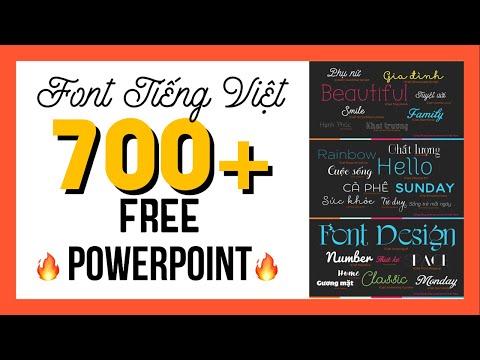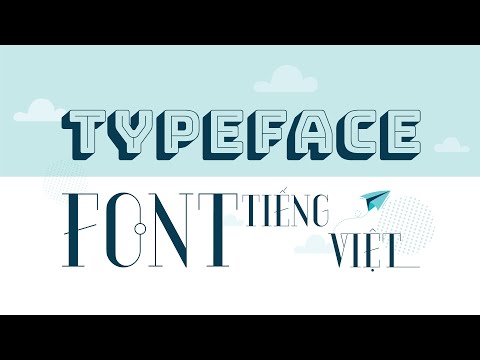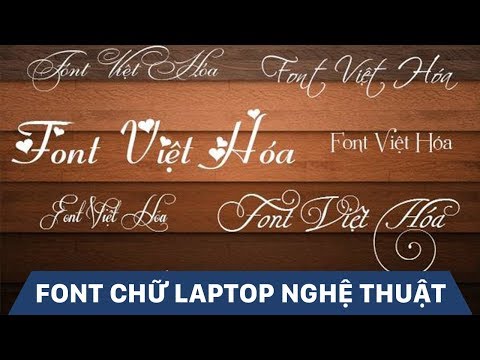
Tổng hợp các font chữ tiếng Việt đẹp trong Word update 2022
Novelty (font cách điệu): Tự nhiên, vui vẻ. Grunge (font bụi bặm): Mạnh mẽ, bí ẩn. Tặng bạn : 99+ Mẫu Font chữ làm biển quảng cáo. Font Chữ Tiếng Việt Đẹp Cho Thiết Kế giúp cảm nhận của người xem tốt
Dec 14, 2021100+ font chữ đẹp, hỗ trợ Tiếng Việt cho Word, Excel, Photoshop. I. Font văn bản 1. Be Vietnam. Đây là font chữ đơn giản với những nét chữ được thiết kế một cách tối giản nhất, phù hợp với
6 days agoFont Maung Việt hóa - 1 em font tuyệt đẹp. Maung Font - 1 kiểu serif hiện đại, mới mẻ và tuyệt đẹp được thiết kế ấn tượng và đặc biệt hơn font chữ còn có thêm các chữ ghép và các chữ xen kẽ
Một số bộ Font chữ khác. Cũng là một bộ font tiếng Việt, Font TCVN3 là một bộ font khá nổi tiếng ở thời gian hiện tại với năng lực thích hợp cao với những bộ gõ tiếng viet như Vietkey, Unikey, đáng qu
Font Việt hóa là một trong những từ khóa được tìm kiếm khá nhiều trên google. Có nhiều font chữ Việt hóa hiện đại, đẹp và ấn tượng. Gõ tiếng Việt bằng cách nào? Bạn có thể sử dụng nhiều phần mềm hỗ tr
Trong việc chọn font tiếng Việt cho website, thường có 3 loại người:. Loại 1, chấp nhận một vài font tiếng Việt mặc định như Arial, Times New Roman… và không có nhu cầu thay đổi gì hơn. Loại 2, cảm th
Jun 2, 2021Font Tiếng Việt Photoshop. Thiếu phần lớn bộ font chữ đẹp đến Photoshop đã khiến cho tác phđộ ẩm xây đắp của doanh nghiệp trsinh sống nên 1-1 điệu và không tồn tại sức lôi kéo. Nếu ai đang